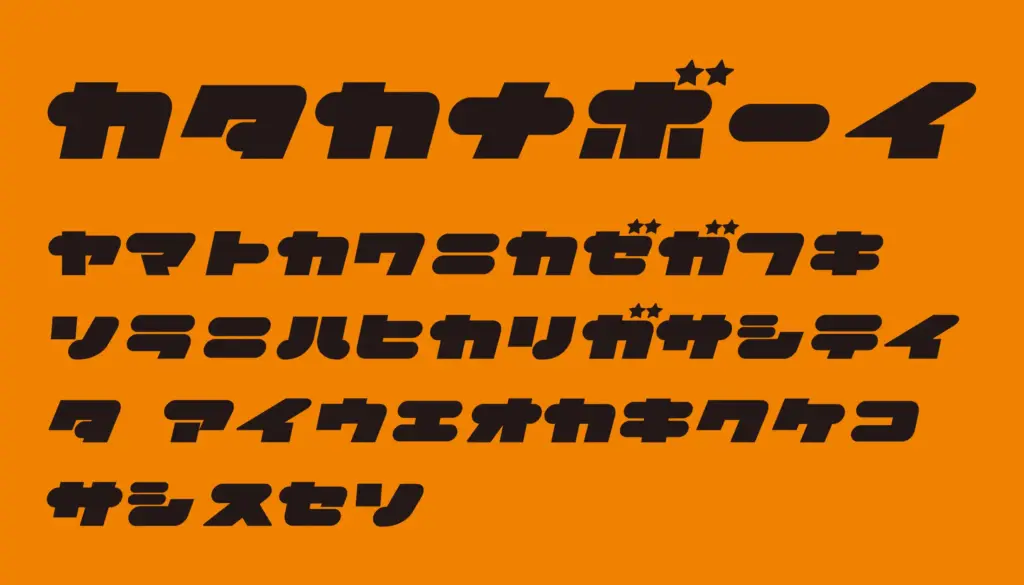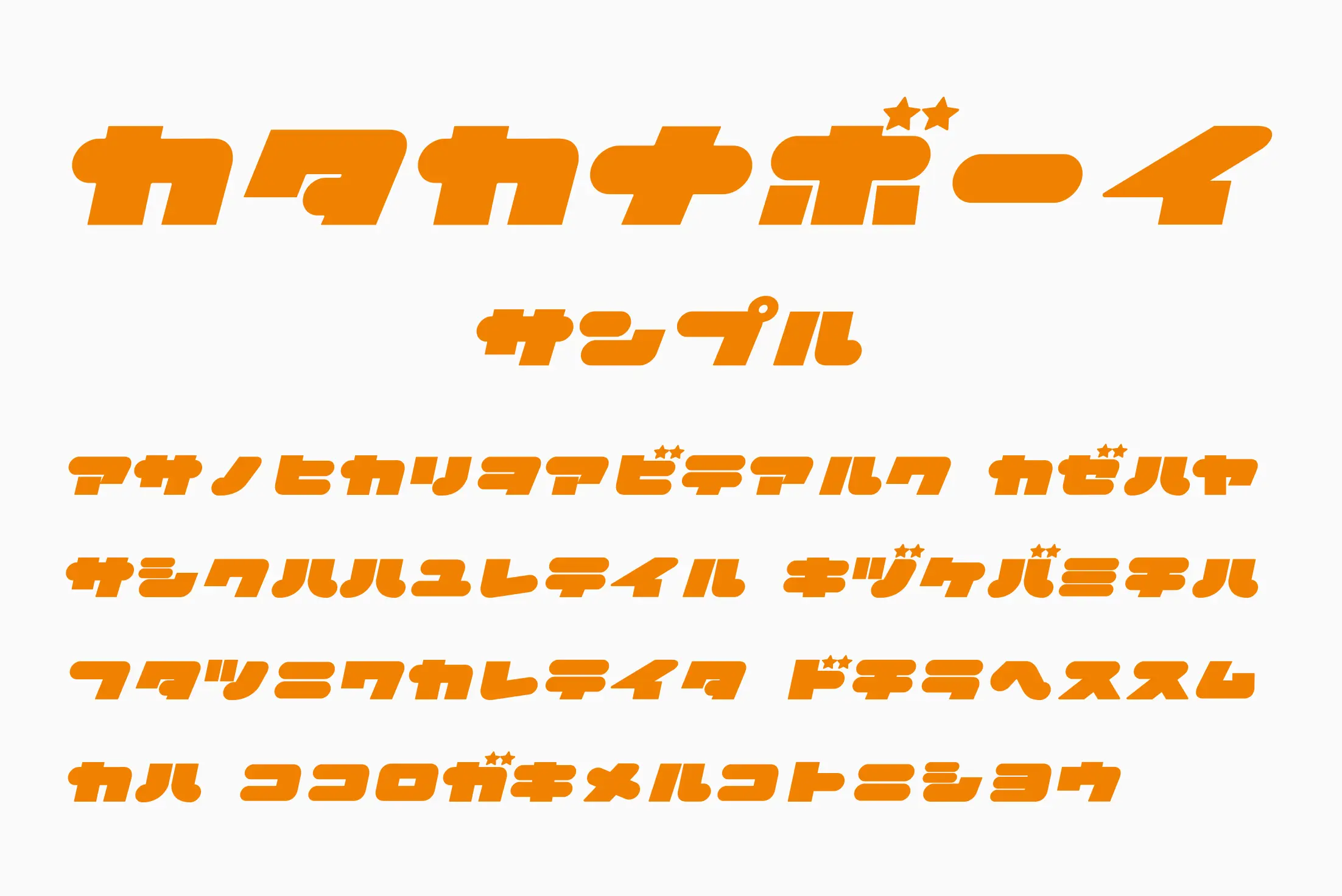
カタカナボーイ 角丸かつ極太な文字に、濁点部分は★(星)モチーフを採用し、80〜90年代のアメリカンレトロ感や少年冒険イメージを演出。テレビ番組やアニメタイトル、Webバナーなど、強い個性と遊び心を求めるデザインにぴったりです。 カテゴリ OS Windows/Mac OS 形式 OpenType 収録文字 カタカナ 商用 商用利用可 配布サイト こちら ※利用規約は必ずお読みください フォントをダウンロードする 類似フォント一覧 マスキングデコラ 左手で書いたぐにゃりフォント わたあめ 好きを届けるフォント「大大大大だぁい好き」 おやつぽっけフォント GWノート手書きかな したたる明朝初号 デビルのしっぽ